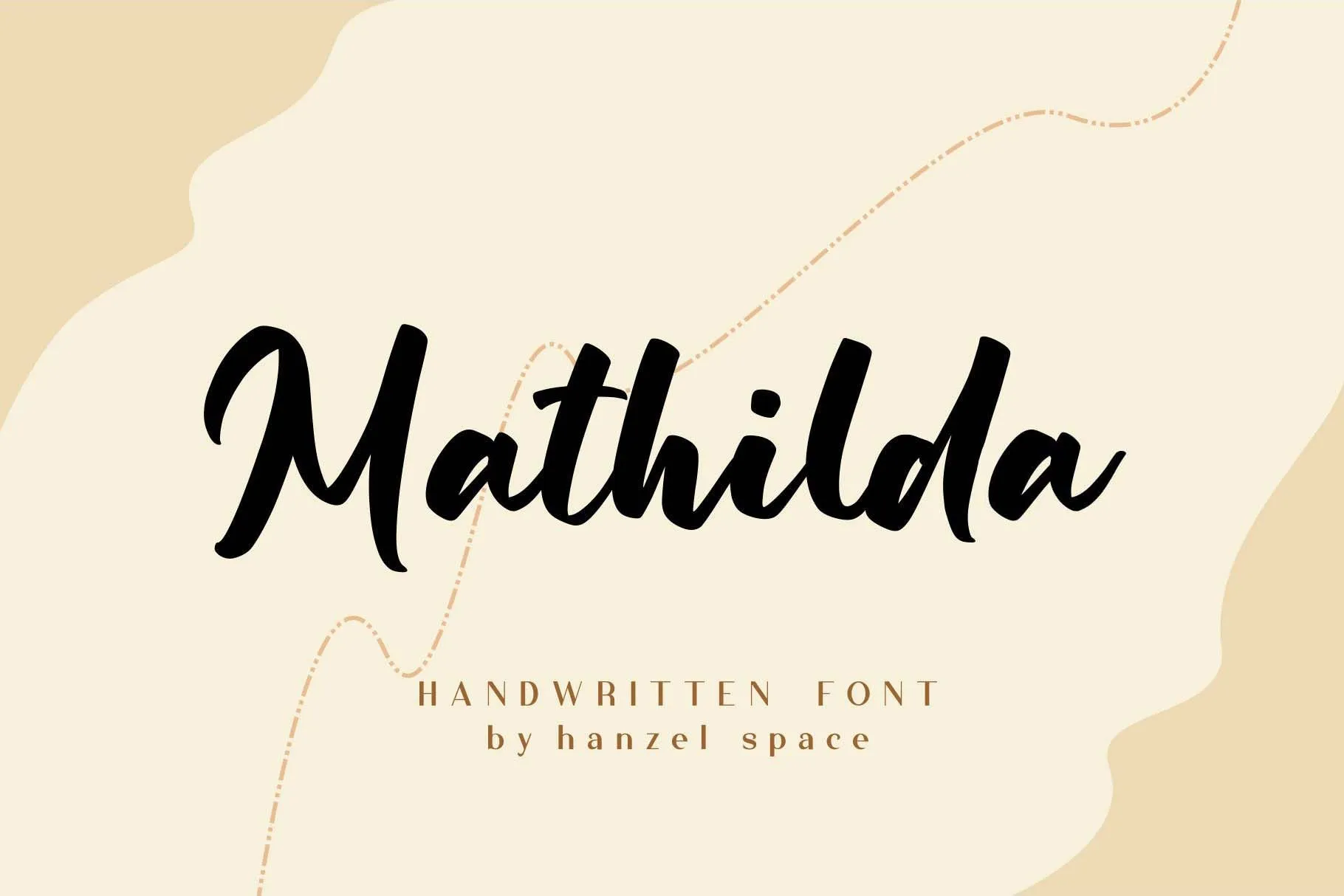
Mathilda Font – Download Grátis
A Mathilda Font é uma escolha perfeita para designers que desejam adicionar um toque contemporâneo e criativo a suas criações digitais. Esta tipografia script moderna, com sua consistência suave de pincel, oferece uma sensação orgânica e dinâmica, ideal para criar letras à mão fluidas. Com seu estilo energético e vibrante, é perfeito para quem busca um recurso visual atraente que atinja diferentes públicos. Sua proposta como fonte script, projetada para ser uma combinação poderosa de design e funcionalidade, torna-a irresistivelmente atraente. Perfeita tanto para textos de layout gráfico quanto para designs digitais em geral, o Mathilda Font é um ícone da categoria de fonts scripts, oferecendo um estilo singular que se destaca entre as opções disponíveis.